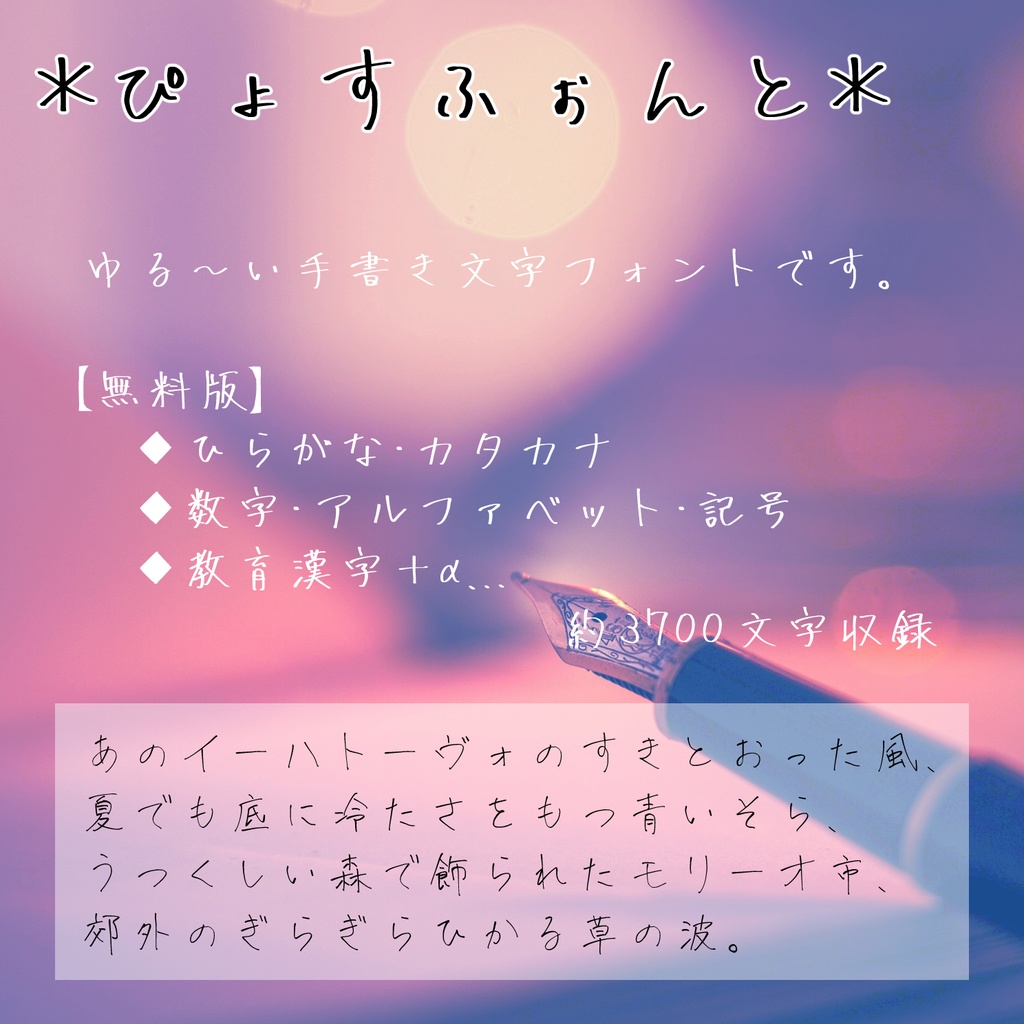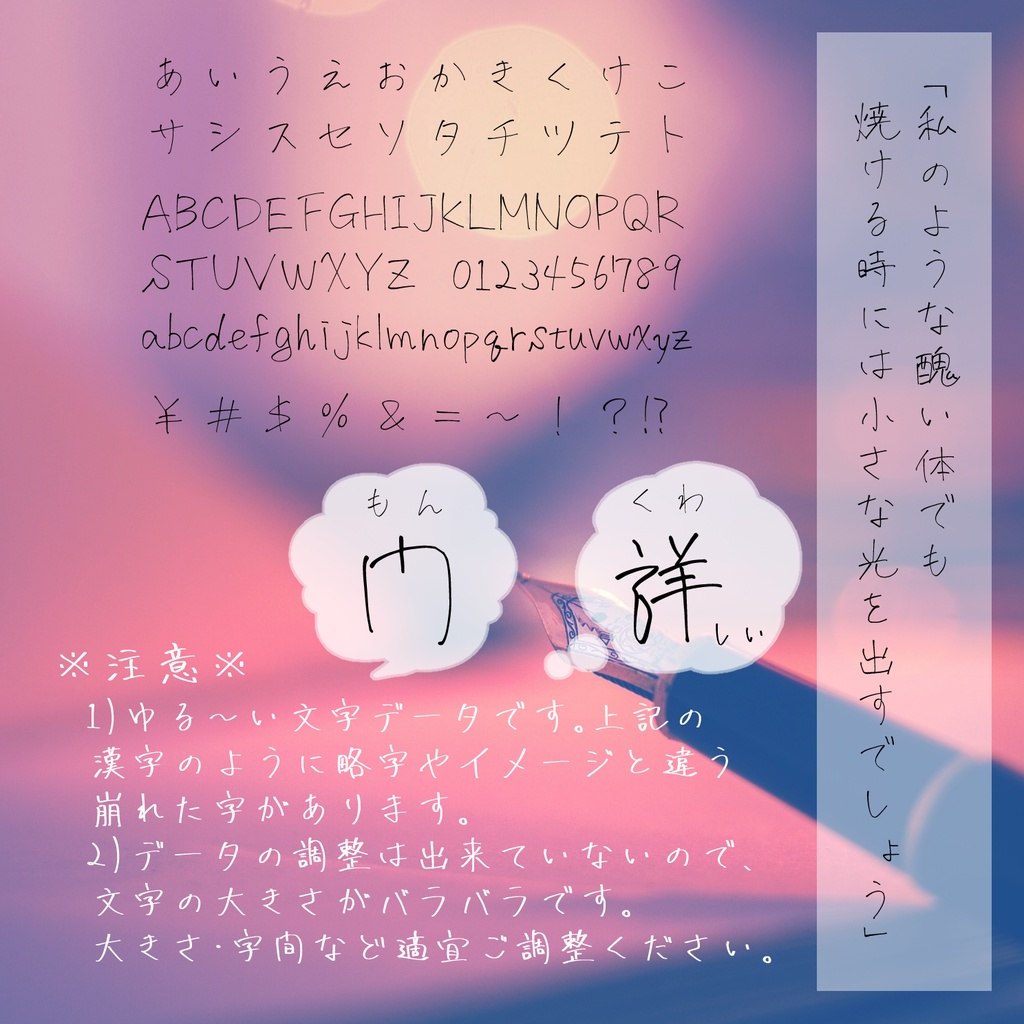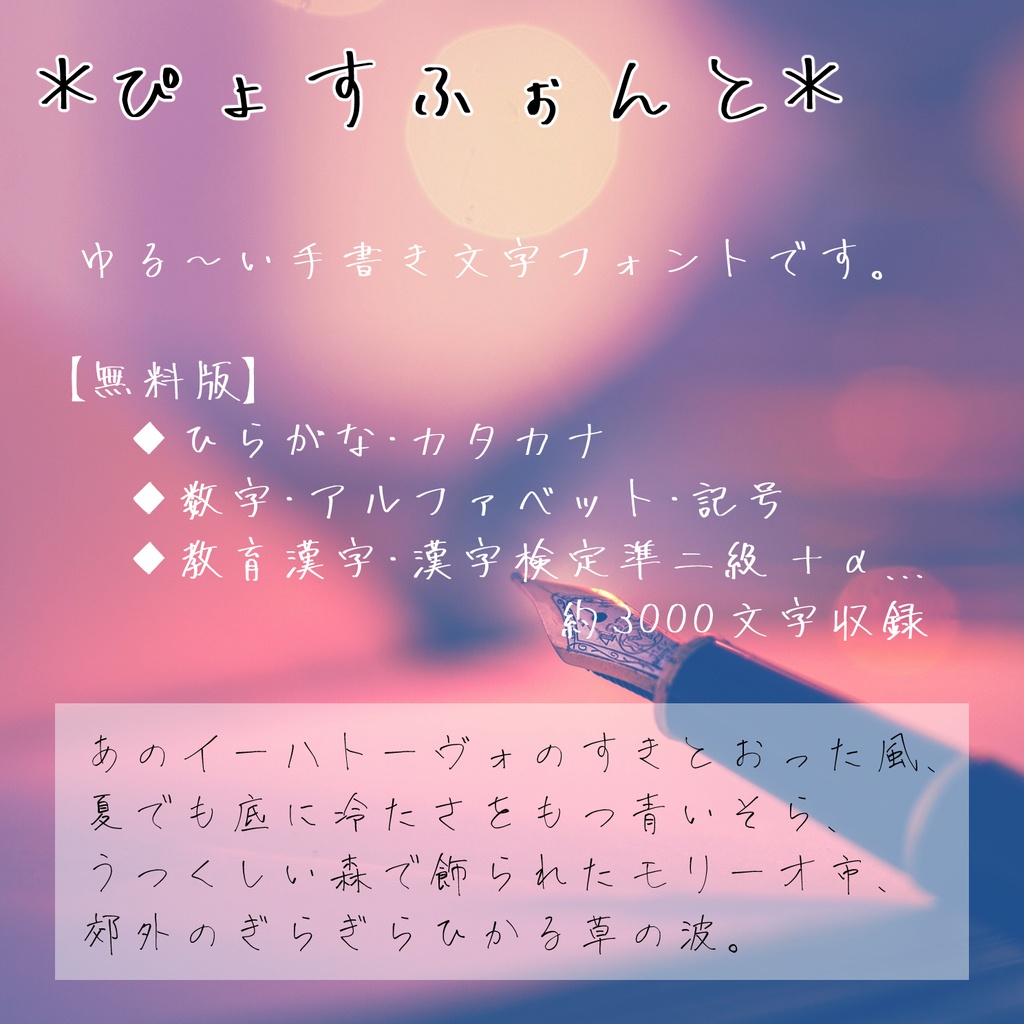
手書きフォント「ぴょすふぉんと」無料版
自分の文字をそのままフォントにした、ゆる~く雑な、そして決して上手くはないのが味のフォントです。 字の書けない時・書きたくない時用に…とぼんやり書き溜め始めた文字がなかなかの文字数になったので、自分用だったものを配布してみます。 使いやすいものではないので、試してみるか…という方向けです。 よろしければどうぞお使いください。 「ぴょすふぉんとふりぃ」(無料版) ・形式:Open Type ・収録字数約3,700字、漢字検定準二級程度まで+α(JIS第一・第二水準はまばら収録) ・フォントを描こう!(https://buttaiwan.github.io/writemyfont/ja.html)を使って作成しております。 ・上記サービスを利用している兼ね合いもあり、データの細かい調整は出来ておりません。字間・大きさ等、適宜調整しながらの利用が必須の内容物です。 DL後、フォルダ内部の「Read me.txt」もご確認ください。 ======ご利用にあたって====== 商用・非商用問わず無償で利用可能です。 また、本フォントの著作権の放棄はしておりません。 自作発言やデータの改変、二次配布などはご遠慮いただきますようお願いいたします。 【OK】 ・イラスト等の製作物(同人誌などの二次創作物を含む) ・印刷物(ポスター、フライヤー、名刺など) ・Webサイト・広告バナー・SNS配信 ・動画、配信用グラフィック ・アプリ・ゲーム内での使用(画像化・アウトライン化済みのもの) ・ロゴ制作(※非常~~~にロゴに向かないデータという意味で推奨はしません) 【NG】 ・本フォントを含むロゴでの商標登録 ・違法・迷惑行為など公序良俗に反するものへの使用 ・自作発言 ・二次配布(有償、無償を問わず禁止) ・フォントデータ自体の改変 その他、ご不明な点がございましたらお問い合わせください。 必要に応じてガイドの内容を変更することがあり、公開後は最新版が適用されます。 また、予告なく本フォントデータの更新、配布停止をすることもございますのでご了承ください。 ================================================ 更新履歴 2026/5/13 データをver1.2にアップデート(「水」の誤字を修正) 2026/4/16 利用規約の変更・追記 データをver1.1にアップデート(3000→3700文字収録) 2025/12/26 ver1.0公開 ================================================